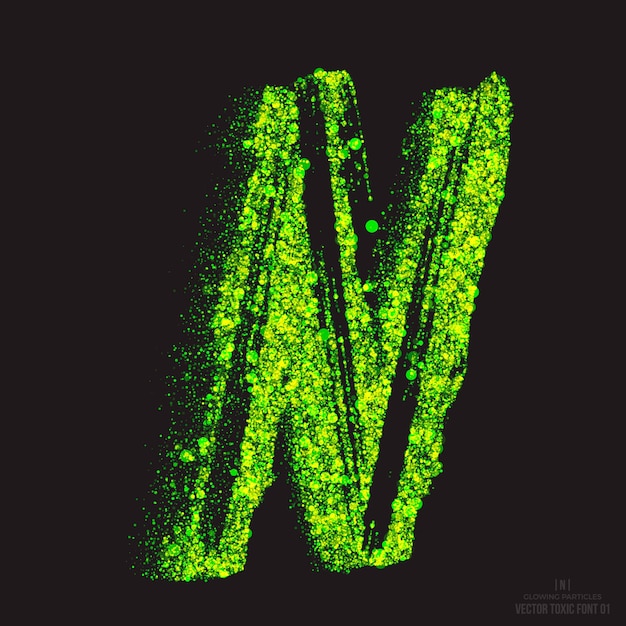
Lettre N Effet De Texte Toxique Grunge. Acide Font Abstract Glowing Bright Green Color Particules Isolées Sur Fond Noir. Déchet radioactif. Horreur Zombie Apocalypse. Élément de conception de symbole de flamme verte